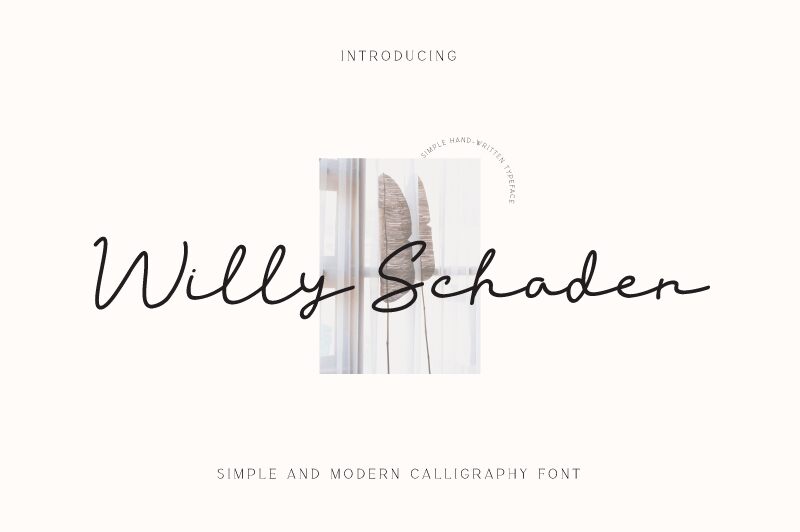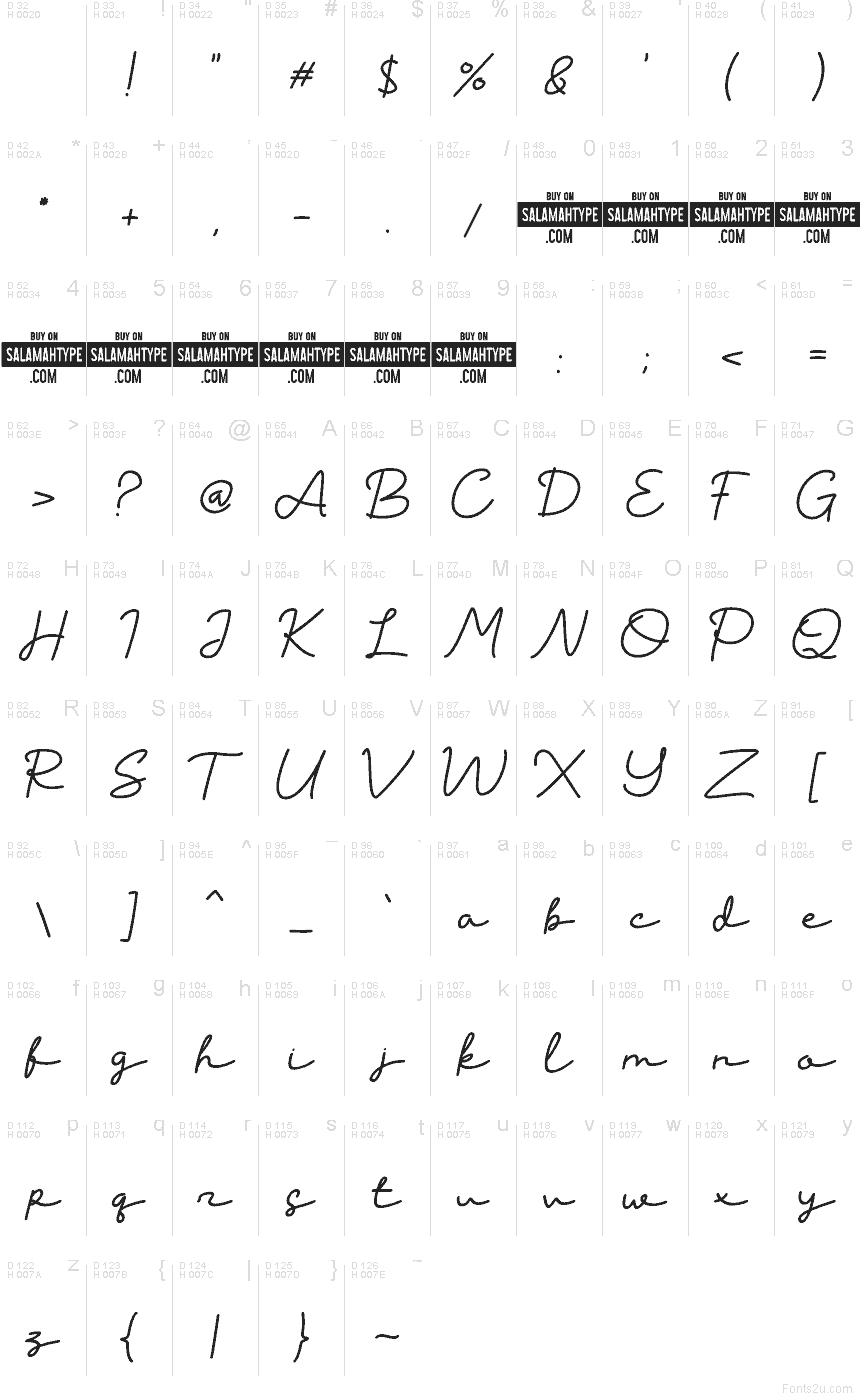
Willy Schaden von Salamahtype ist eine kostenlose Handschrift-Schrift, die durch einen weichen, fließenden Rhythmus besticht. Die hohen Schleifen und abgerundeten Schwünge verleihen der Schrift eine gewisse Leichtigkeit, während die langen Verbindungen an eine dynamische Handschrift erinnern, die mit einer einzigen, selbstbewussten Geste aufs Papier gebracht wurde.
Dieser natürliche Fluss eignet sich perfekt für Unterschriften, Boutique-Logos, Produktverpackungen, Einladungstexte oder Social-Media-Zitate – überall dort, wo eine persönliche Note wichtiger ist als strenge Formalität. Dank der schwungvollen Bewegung kommt die Schrift auch bei kurzen Markennamen und personalisierten Designs hervorragend zur Geltung und sorgt für eine klare Präsenz, ohne steif zu wirken.